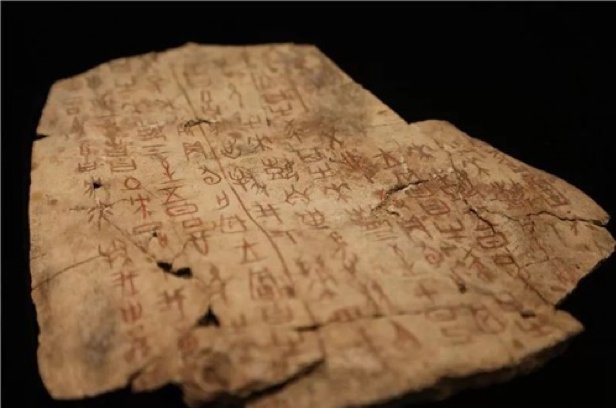
【原文标题:认出1个字,奖励10万元!甲骨文,是如何被“读”出来的?】
今年是甲骨文发现和研究120周年。120年,对于每个人来说都是难以企及的时间跨度,然而对三千多岁的甲骨文而言,不过弹指,历久弥新。
甲骨文是迄今为止中国发现的年代最早的成熟文字系统,在已知的四大古文字体系中,唯有以殷墟甲骨文为代表的中国古文字体系,一脉相承,绵延至今。
据记载,从1899年甲骨文首次发现,现在分布在全世界的甲骨文收藏估计在13万到15万片之间,总共记载的字数达到4300余个。但目前,甲骨文的释读仍处在瓶颈期,仍有一大半的字有待破解。
只有破解文字,才能读懂历史。甲骨文释读不仅对中国学者,乃至对全世界古文学者都是极大的挑战。为了能够尽快解开每个甲骨文字背后隐藏的文化谜题,暨甲骨文发现研究120周年大庆之际,位于河南安阳的中国文字博物馆日前向海内外公开征集甲骨文释读成果,来破译这一有着3000多年历史的古老文字。
据悉,文化学者只要破译出一个未释读的甲骨文字,经专家鉴定确认后,即可获奖励10万元。2018年,南开大学蒋玉斌教授曾凭论文《释甲骨金文的“蠢”——兼论相关问题》获得一等奖10万元。
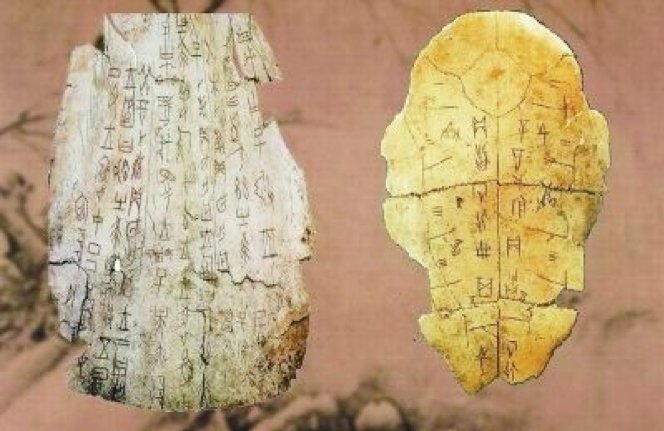
那么,甲骨文是如何被“读”出来的呢?学者们都用什么依据来破译?
我们先了解一下甲骨文发现的过程。
甲骨文最早发现于1899年。相传,清末国子监祭酒王懿荣到中药房抓药,意外发现了一味药材“龙骨”有很多划痕,类似篆文。而王懿荣正好是清末一位酷爱金石、热衷收藏、兼通中医的学者。他很快意识到,这很可能是一种古老的文字。
于是,王懿荣开始着手通过多种方式搜集这种有特殊符号的“龙骨”,短短时间内竟然积攒了1500多片。但遗憾的是,他还没开始研究,就在八国联军进京后自尽殉国。
王懿荣死后,其子为了偿还债务,将大部分“龙骨”出售给刘鹗。刘鹗购得王懿荣旧藏后,开始花费更大的力气收藏甲骨,数年之间已收集了5000多片。
1903年,刘鹗从自己的甲骨收藏中精选墨拓了1058片,以石印本出版了我国第一部著录甲骨文的著作《铁云藏龟》。如果说王懿荣是发现者,那么刘鹗就是甲骨文的开拓者。
在《铁云藏龟》的自序里,刘鹗写出了他认出的40多个字,这也是首批被释读的甲骨文字。但是,刘鹗只是介绍了自己的研究成果,却没有介绍释读的具体方法。
后来,另一位学者孙诒让在研究了甲骨文后,认出了185个字。他使用的方法是:
“略摭金文、龟甲文、石鼓文、贵州红岩古刻,与《说文》古籀互相勘校,揭其歧异,以箸渻变之原,而会最比属,以寻古文、大小篆沿革之大例”。
简单说,孙诒让的主要方法就是古文字字形比较与偏旁分析,这是很经典的文字学研究方法。
到了民国时期,甲骨文研究释读开始大放异彩,出现了著名的“甲骨四堂”。所谓“甲骨四堂”,分别指的是罗振玉、王国维、董作宾、郭沫若,因四人字号中均有“堂”字而得名。
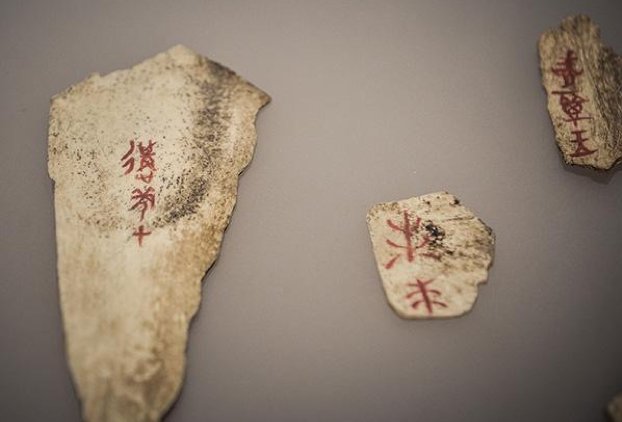
1914年,罗振玉出版了《殷虚书契考释》,标志着甲骨文进入了考释时期。他用了更为简捷的逆推法,从《说文解字》的字形倒推到金文以至甲骨文。他最早释读了一些殷商先王先妣的名号,并反过来用卜辞证实《说文解字》存在的讹误。他一生释读了571个字,占今天所释读全部甲骨文的四分之一多。对甲骨文研究释读成就最大。
1917年,王国维著《殷卜辞中所见先公先王考》及《续考》,甲骨文又进入一个新的史料时期。王国维的研究方法已不偏重于单纯的文字考证,而是将文字放在具体历史语言环境里,结合所有辞例释读甲骨文字。
从数量上看,王国维释读出的文字仅有10来个,远不如孙诒让、罗振玉,但其释读成果却具有非凡的史学价值,大大地推动了商代史的研究。
1933年董作宾发表了《甲骨文断代研究例》,提出甲骨文断代的十项标准,并将甲骨文分为五期。他的主要功力不在于新文字释读,而是将已释读文字甲骨分期断代。
1930年和1931年,郭沫若相继发表了《卜辞中之社会》与《甲骨文字研究》,标志甲骨文研究进入综合论史时代。郭沫若“就诸家所已拓印之卜辞,以新兴科学的观点来研究中国社会的古代”,成为第一个用历史唯物主义研究古文字的学者。
再往后,唐兰与于省吾的出现,更是将甲骨文的考释进行了理论系统化,但同时也是从此开始甲骨文的释读研究开始进入瓶颈期。
至今,甲骨上的3500个文字,也只有过半数被考释出来,而不少地名、人名、族名之类的专名,则难以释读。另外,对于已考释出来的文字,含义理解也存在一定争议。
由此,安阳中国文字博物馆向海内外公开征集甲骨文释读成果,是时代的产物,也将标志着甲骨文研究向新时代跨越和迈进。